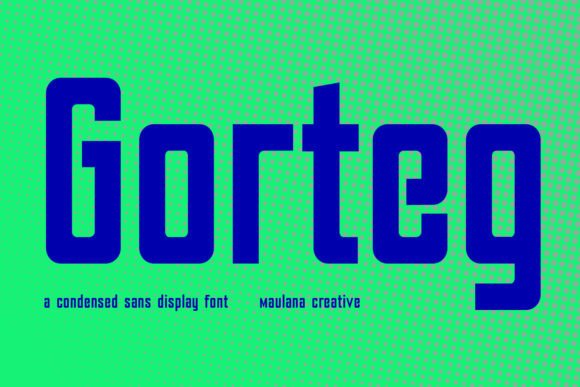
Gorteg Condensed Sans Display Font
Die richtigen Designelemente zu finden, kann eine Herausforderung sein, aber Gorteg Condensed Sans Display Font bietet eine außergewöhnliche Sammlung, die Ihre Arbeit sofort aufwertet.
Egal, ob Sie POD-Produkte (Print on Demand), Hochzeitseinladungen oder Social-Media-Grafiken erstellen, Gorteg Condensed Sans Display Font ist die ideale Wahl.